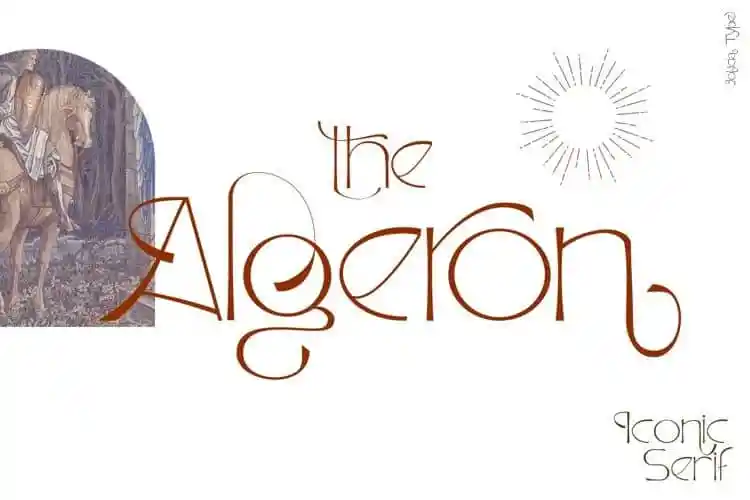
Algeron Serif é uma fonte serif que transmite sofisticação através de suas linhas elegantes e ligaturas elaboradas. Inspirada nos magazines de moda e nas marcas de fragrância, esta font foi criada por Jolicia Type, um designer 99designs. Com seu charcoethé moderno e sua flexibilidade em alternativas personalizáveis, você pode personalizar seus textos para criar um estilo único. Com uma aparência refinada que transmite sofisticação, o Algeron Serif também oferece a opção de usar ligaturas dispostas de forma curvilínea, adicionando ao seu texto um toque singular e autêntico. Este design moderno e elegante é perfeito para ambientes onde você quer transmitir uma mensagem sofisticada ou criar um estilo personalizado. Adotar Algeron Serif como sua fonte permite que você dote seus projetos de um charme atraente e individual, seja em editoriais fashion, embalagens de produtos de luxo ou qualquer outro projeto onde deseja impressionar com elegância. Seja para uma linha de texto única ou para textos interconectados, esta fonte oferece o espaço e as alternativas necessárias para expressar seu próprio estilo.